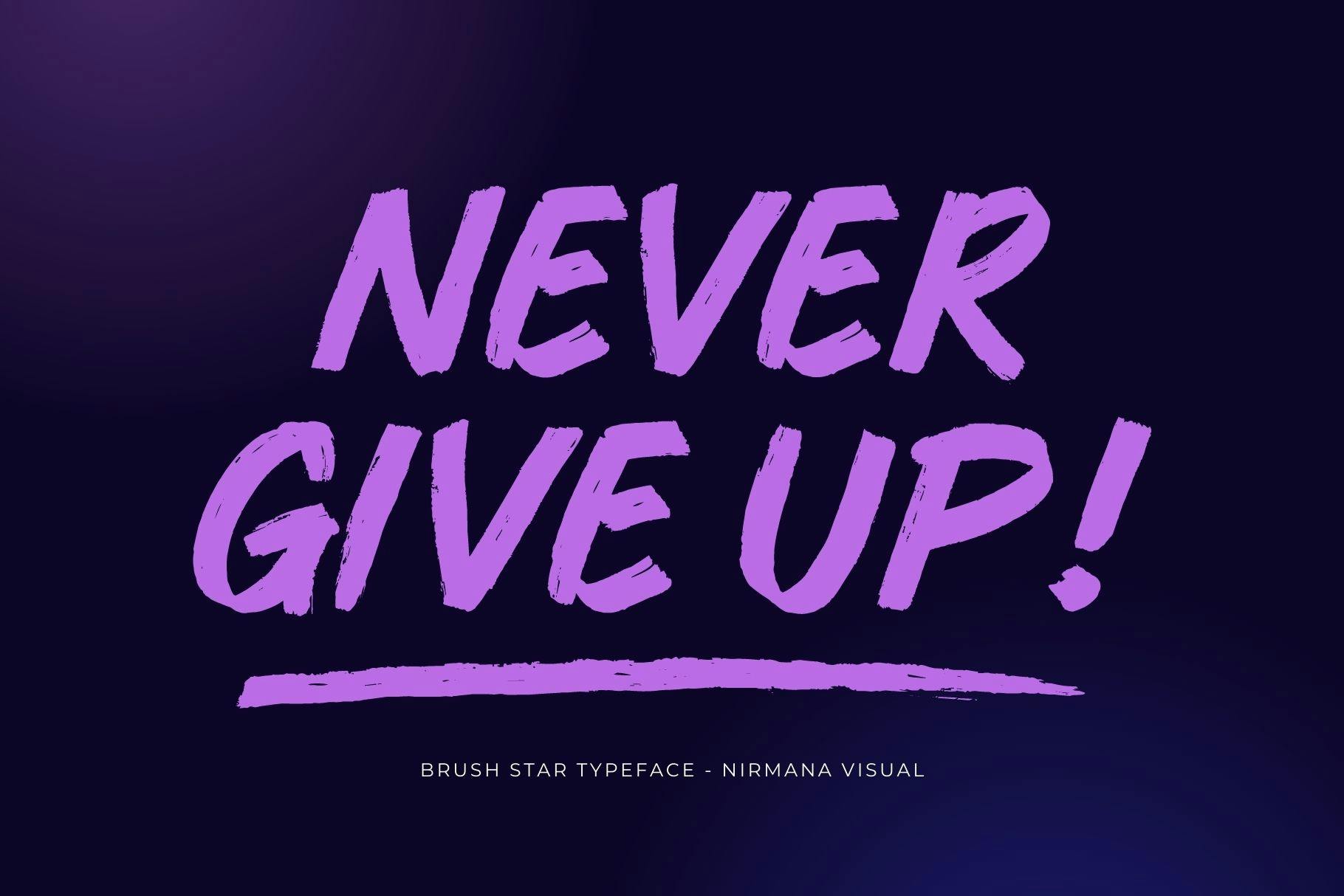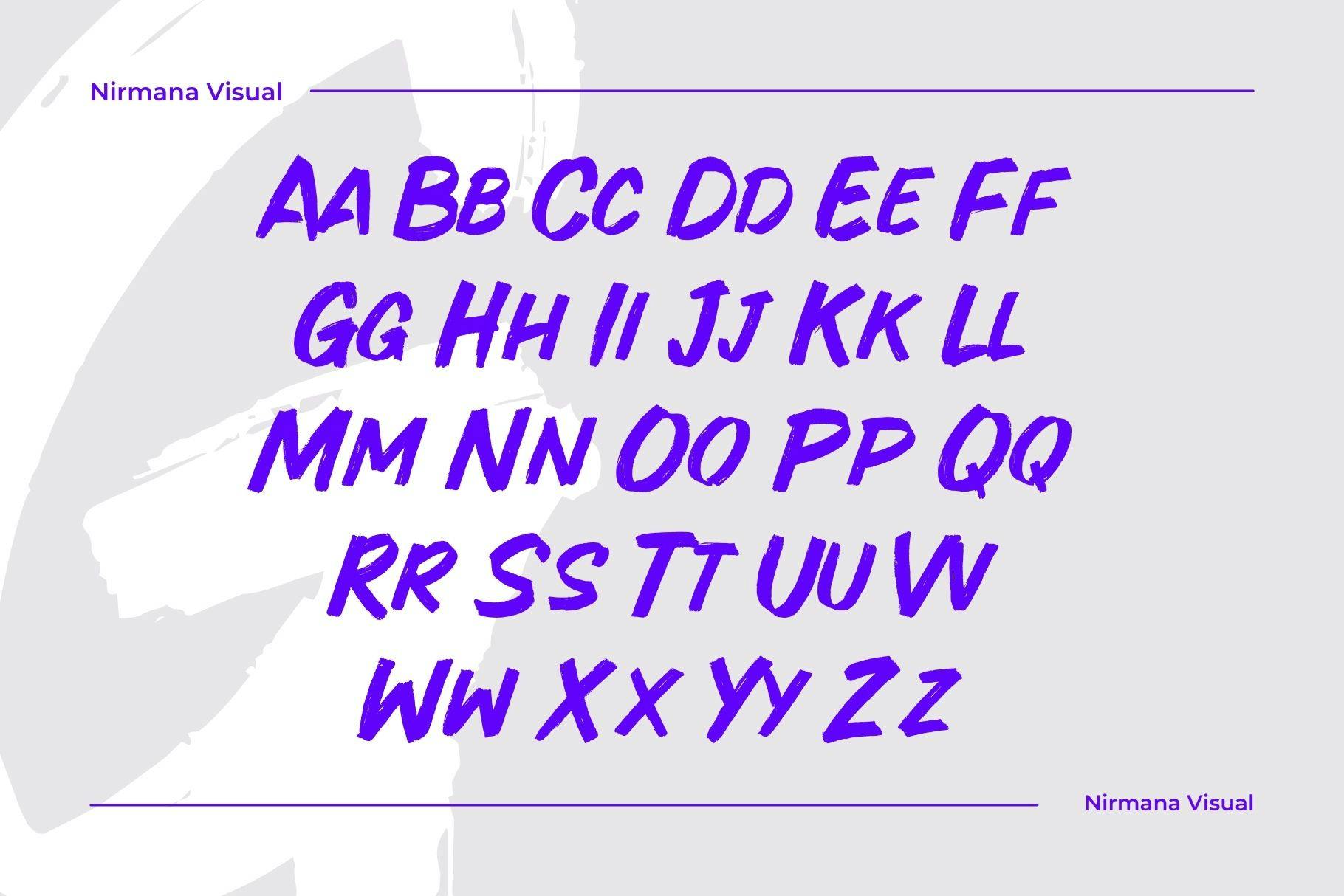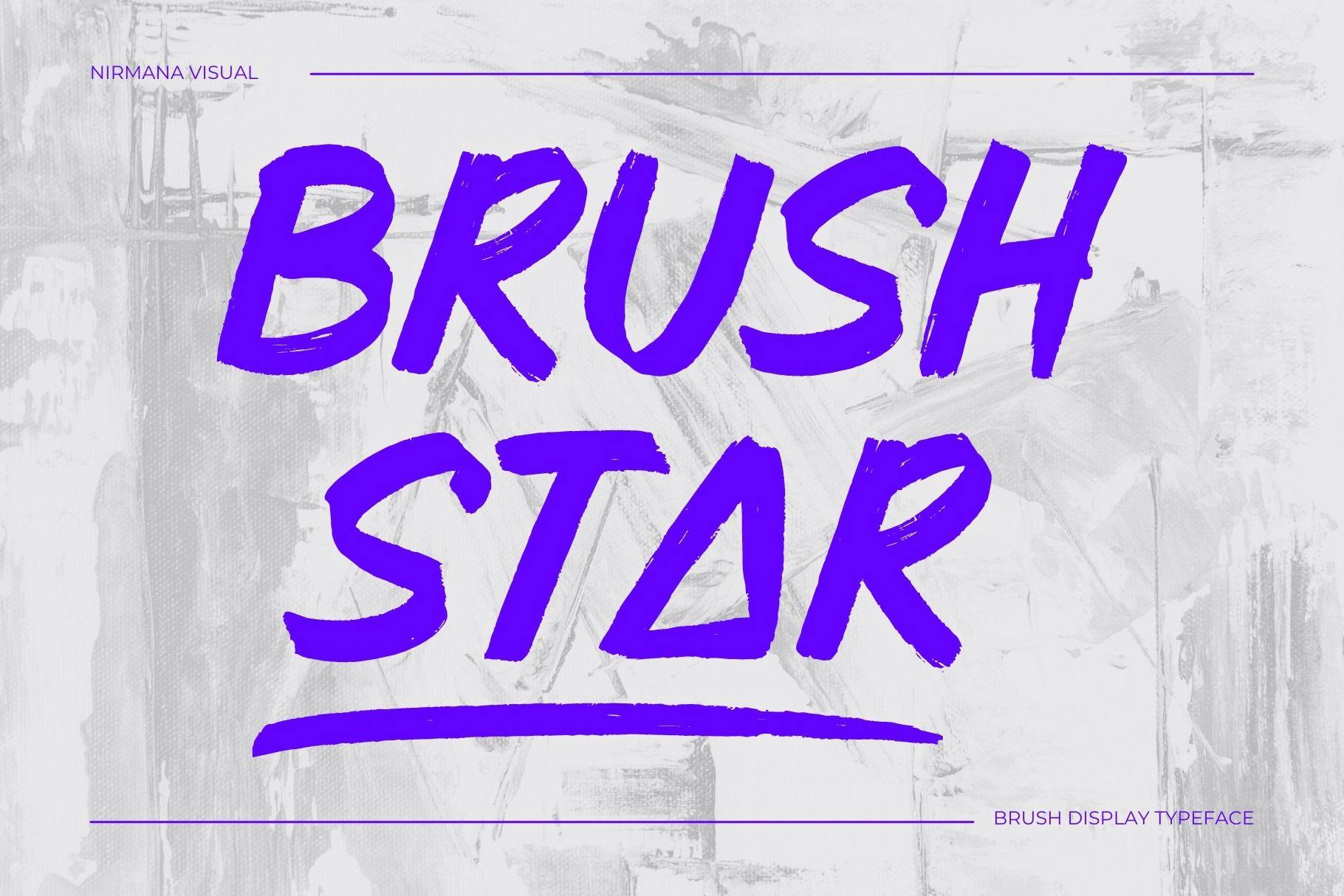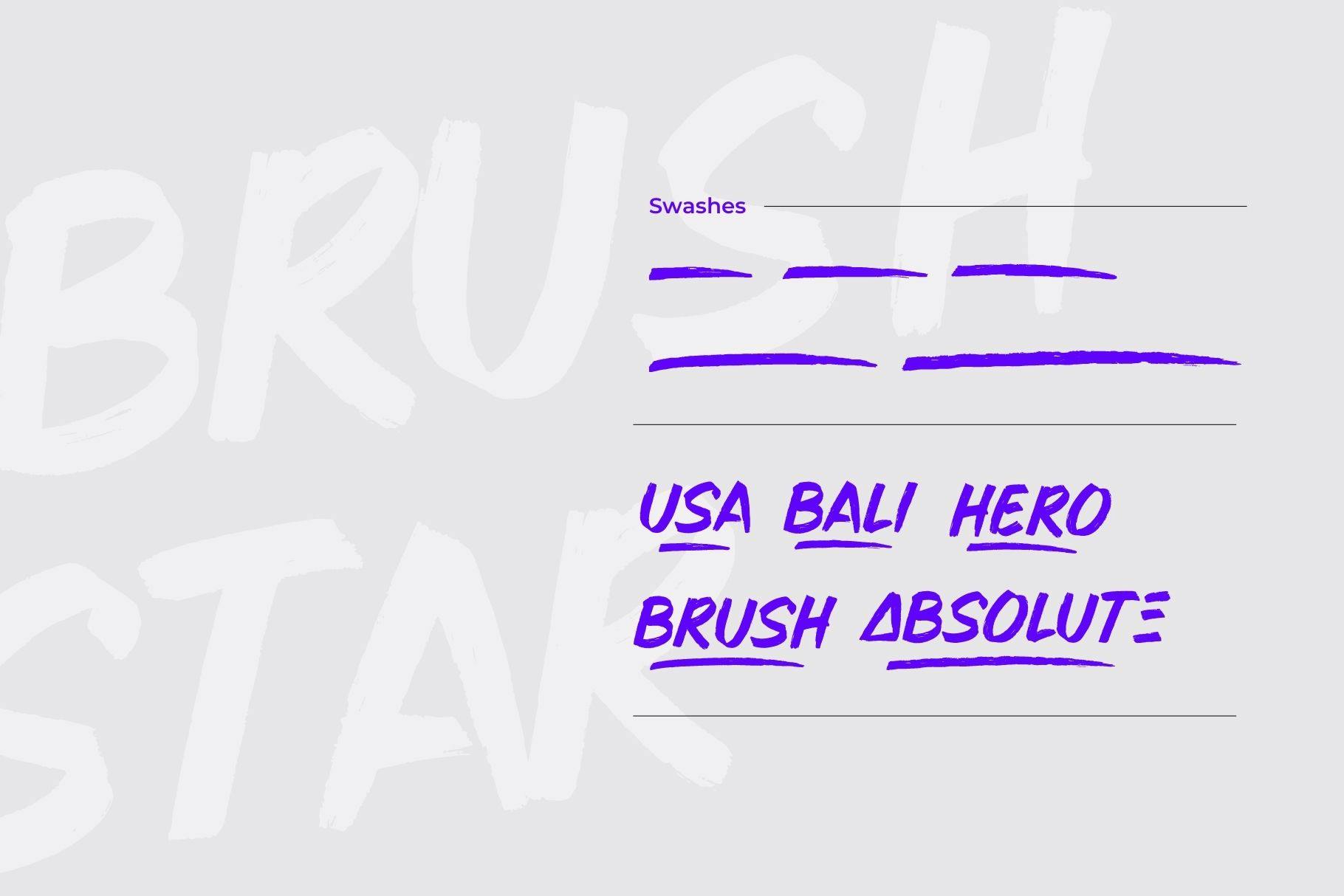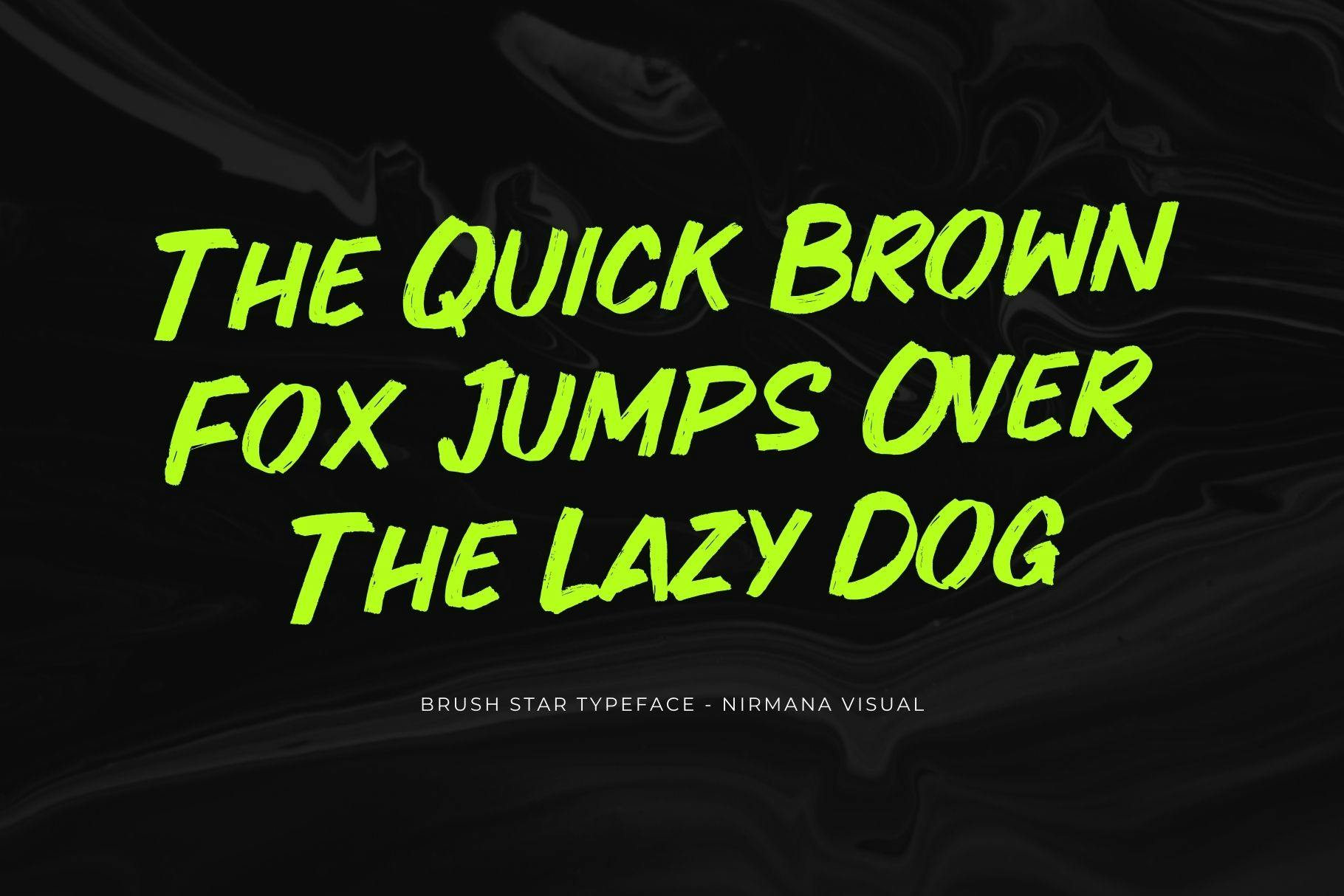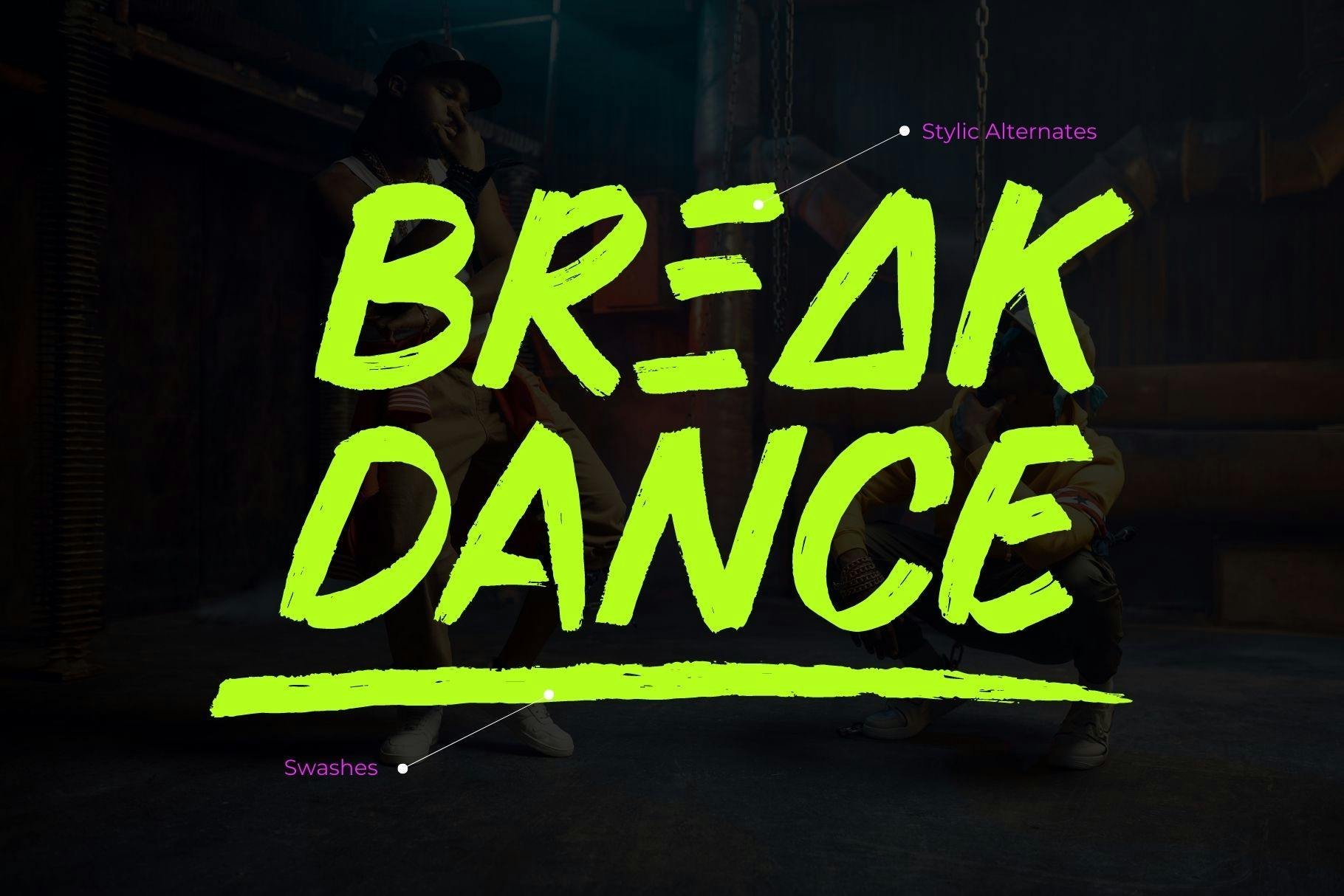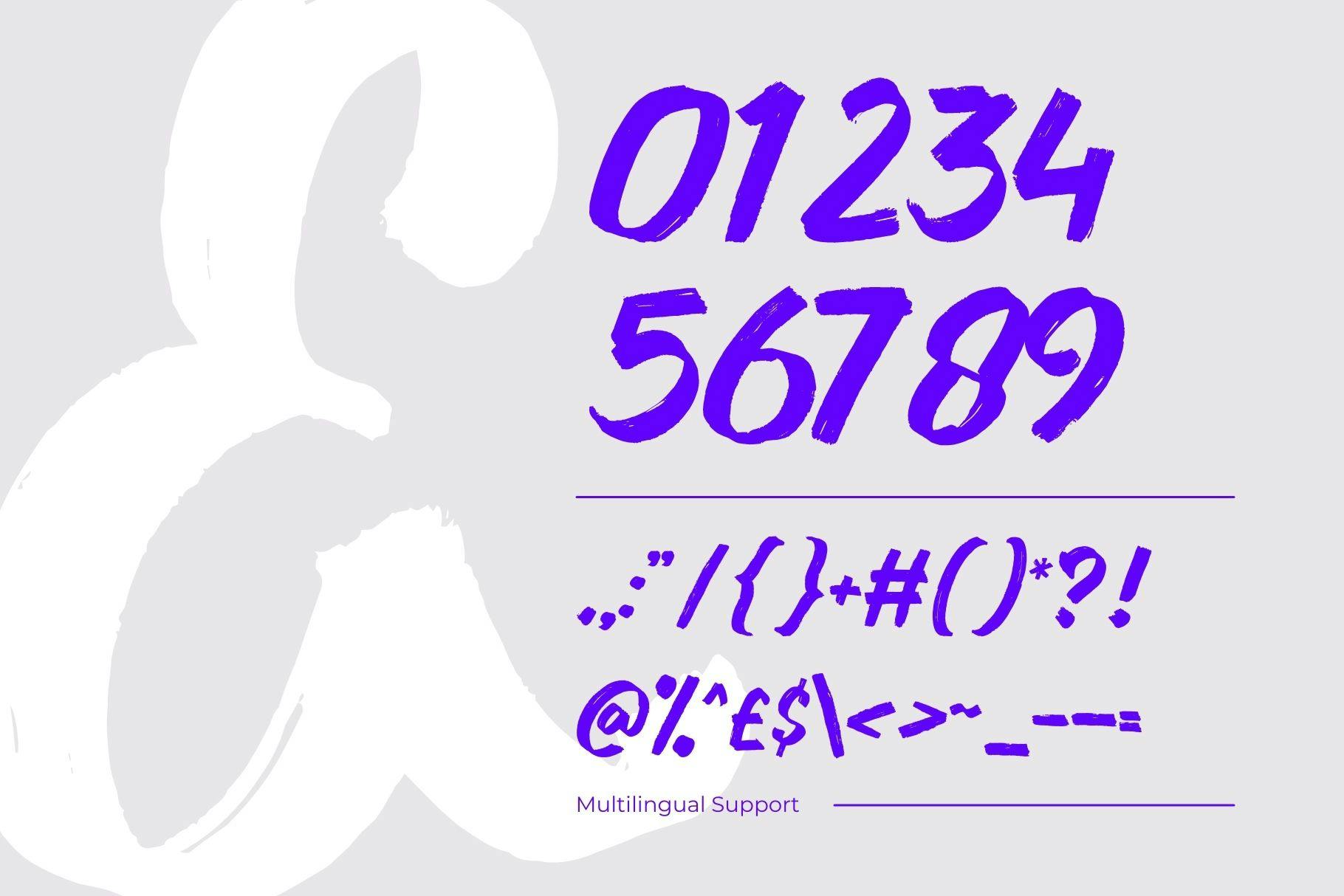
Brush Star یک نوع فونت دستنویس با طراحی خشک است که شامل مجموعه کاملی از حروف بزرگ و کوچک، اعداد و نشانهگذاری، و نمادهای چندزبانه میباشد.
این فونت بهطور خاص برای استفاده در عنوانها، لوگوها، تایپوگرافی، لباسها، مجلات، بروشورها، بستهبندی و بسیاری دیگر از نیازهای طراحی شما مناسب است و طراحیهای شما را مدرن و حرفهایتر میکند.